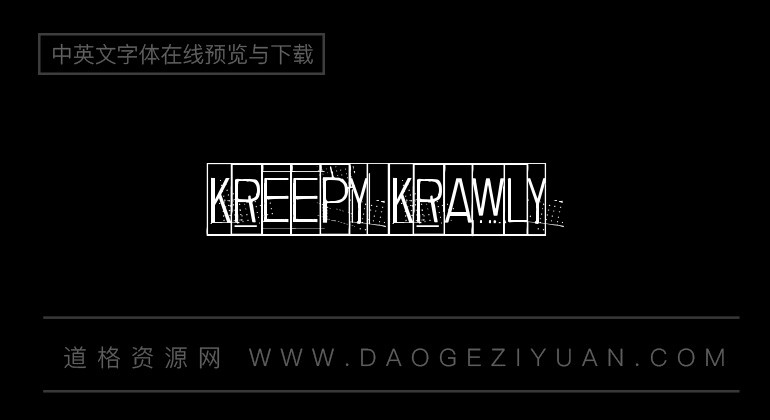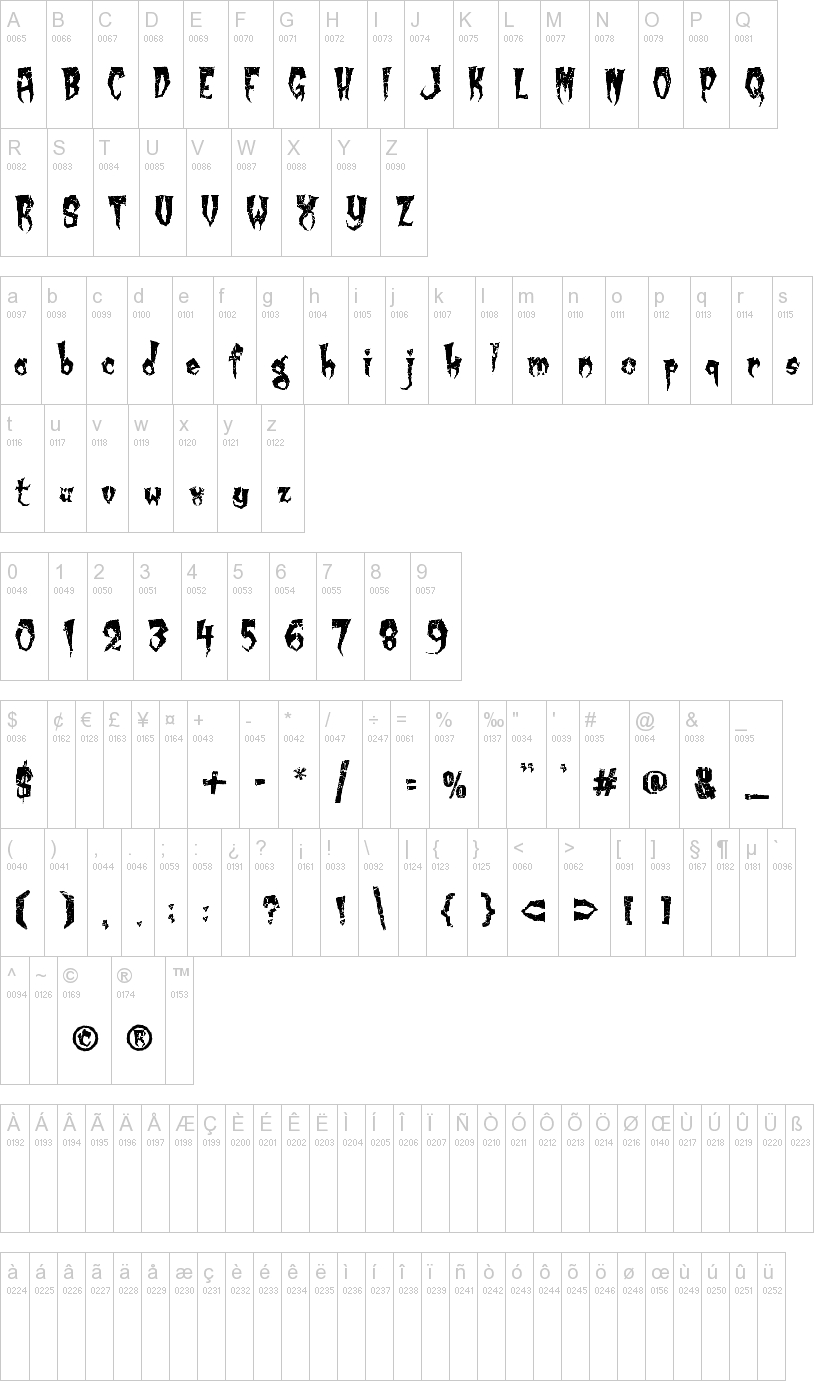
Kreepy Krawly 是一款非常具有表现力的手写体字体,它的字体特点是具有独特的曲线,每个字母的字体都有自己的独特的设计,使用它可以创造出一种温暖的情感,而且这种字体也可以用来表达更多的情感,比如激动,愤怒,悲伤等等。Kreepy Krawly 是一款非常适合用于表达情感的字体,它可以带给你不同的情绪,使你的文本更加有感染力。内容介绍
Kreepy Krawly是一款非常不错的手写艺术字体,具有很好的视觉感,适合于文化类的宣传设计、商业类品牌的广告和产品包装设计以及个性化文字排版等较多场景。